Una vez más, Twitter, una de las redes sociales más usadas ha cambiado de diseño, en esta ocasión específicamente su tipografía.
El nuevo diseño de Twitter no solo incluye su tipografía -lo más destacable-, sino también el alineado a la izquierda y botones con contraste.
El nuevo diseño de Twitter ha comenzado a aparecer desde el pasado miércoles 11 de agosto a algunos usuarios de la red social.
Esto tanto en sus versiones de escritorio como en la de su aplicación para móviles e, incluso en su cuenta oficial han anunciado parte de estos cambios en su diseño.
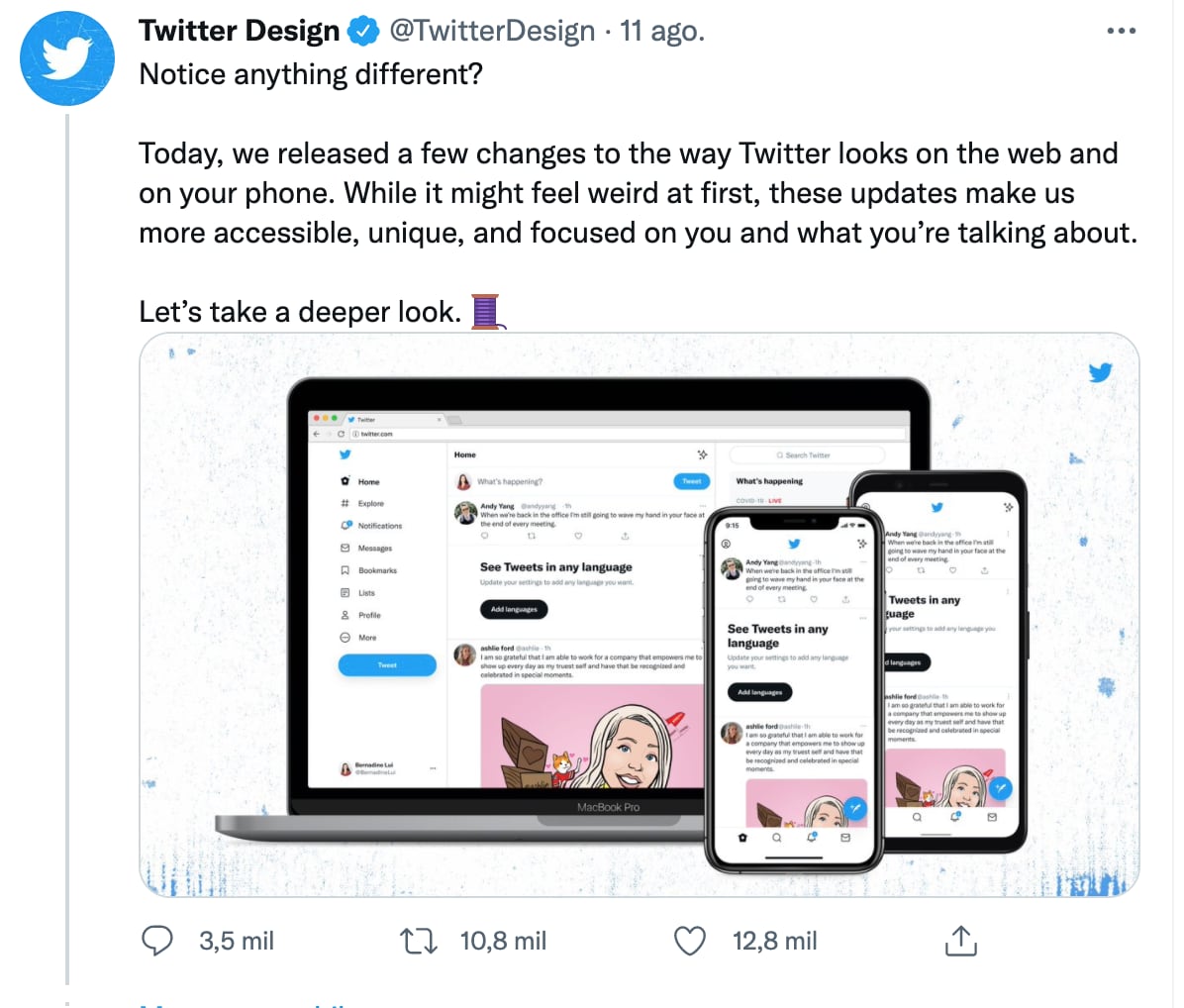
La tipografía de Twitter hace su debut
Como se mencionaba anteriormente, uno de las novedades más destacables en el nuevo diseño de Twitter ha sido su tipografía.
Esta ha sido llamada Chirp y fue anunciada a principios de año y que se alinea a la izquierda en todos los idiomas occidentales.
Esto para que sea más sencillo de leer a los usuarios al momento de ir bajando por el feed de Twitter.
Una de las cosas más notables en la nueva tipografía de Twitter son las líneas más delgadas que aparentemente, permitirán una mejor lectura.
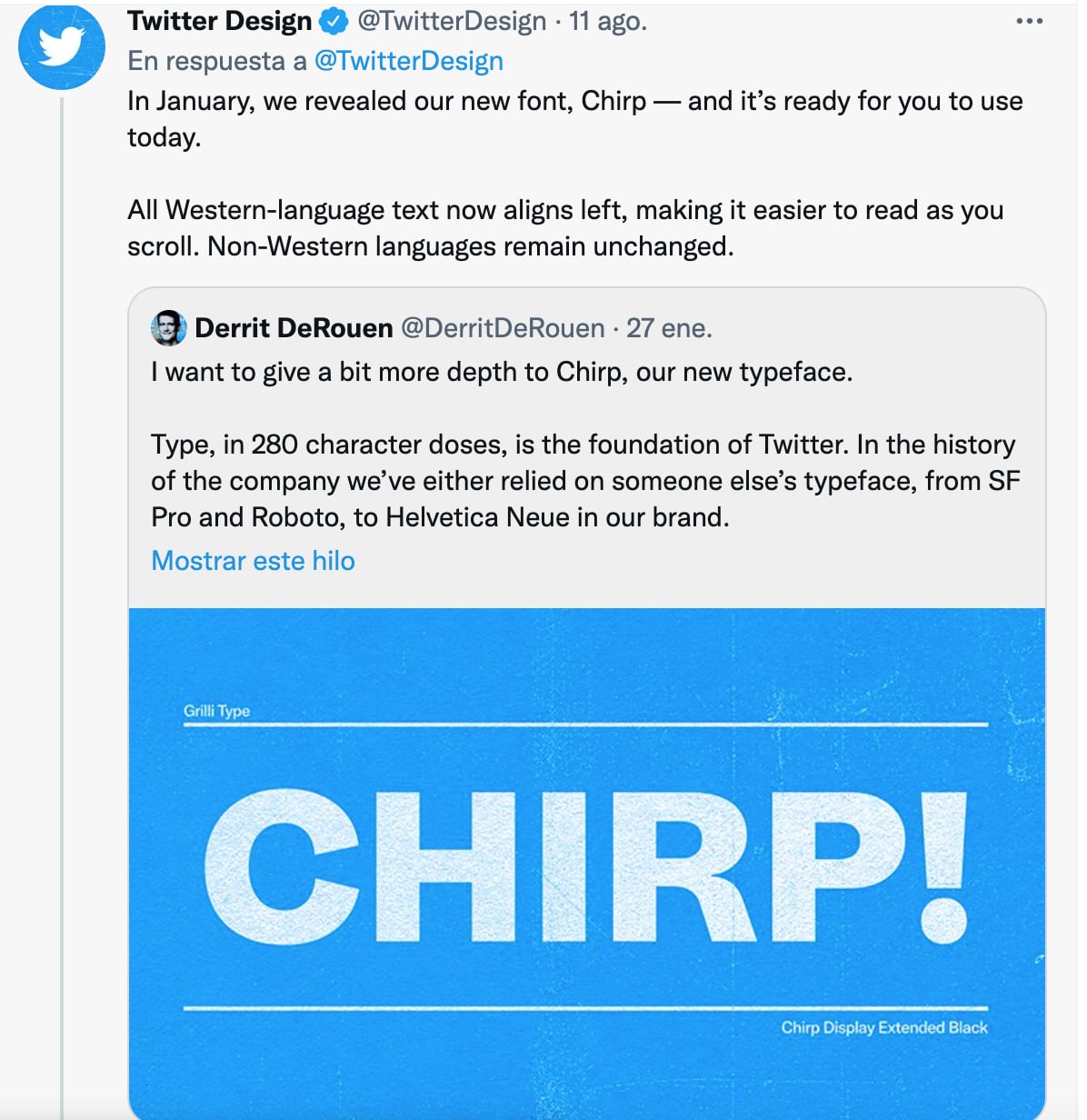
Los colores y contrastes en Twitter permiten al material audiovisual mayor protagonismo
El color también ha sido otro de los cambios de diseño de Twitter, pues usa contrastes altos y reduce el uso del azul.
Esto da mayor protagonismo a las fotos y videos de los usuarios, además de los botones como el de ‘seguir’ que pasan a un contraste alto.
El nuevo diseño de Twitter pretende reducir la carga visual a los usuarios con menos grises y líneas de fondo de división innecesarias.
Asimismo, ha incrementado los espacios entre párrafos para que resulte más sencillo leer textos y se ha anunciado una nueva paleta de colores para personalizar Twitter.